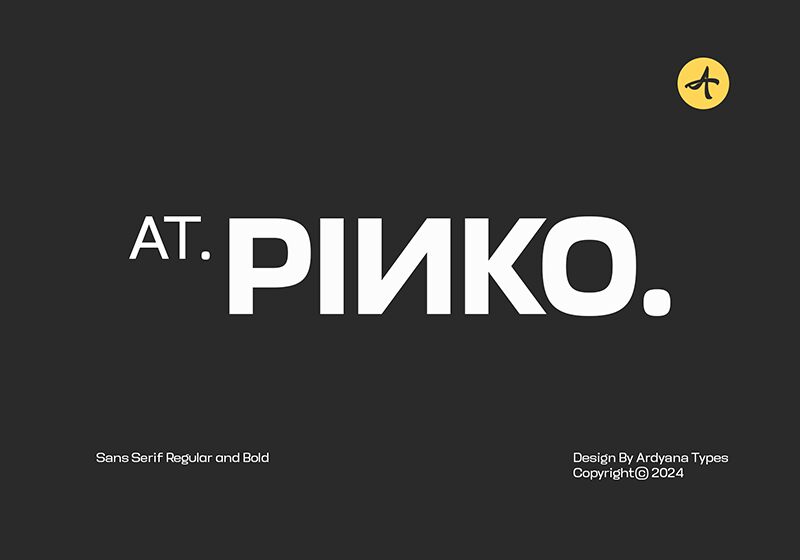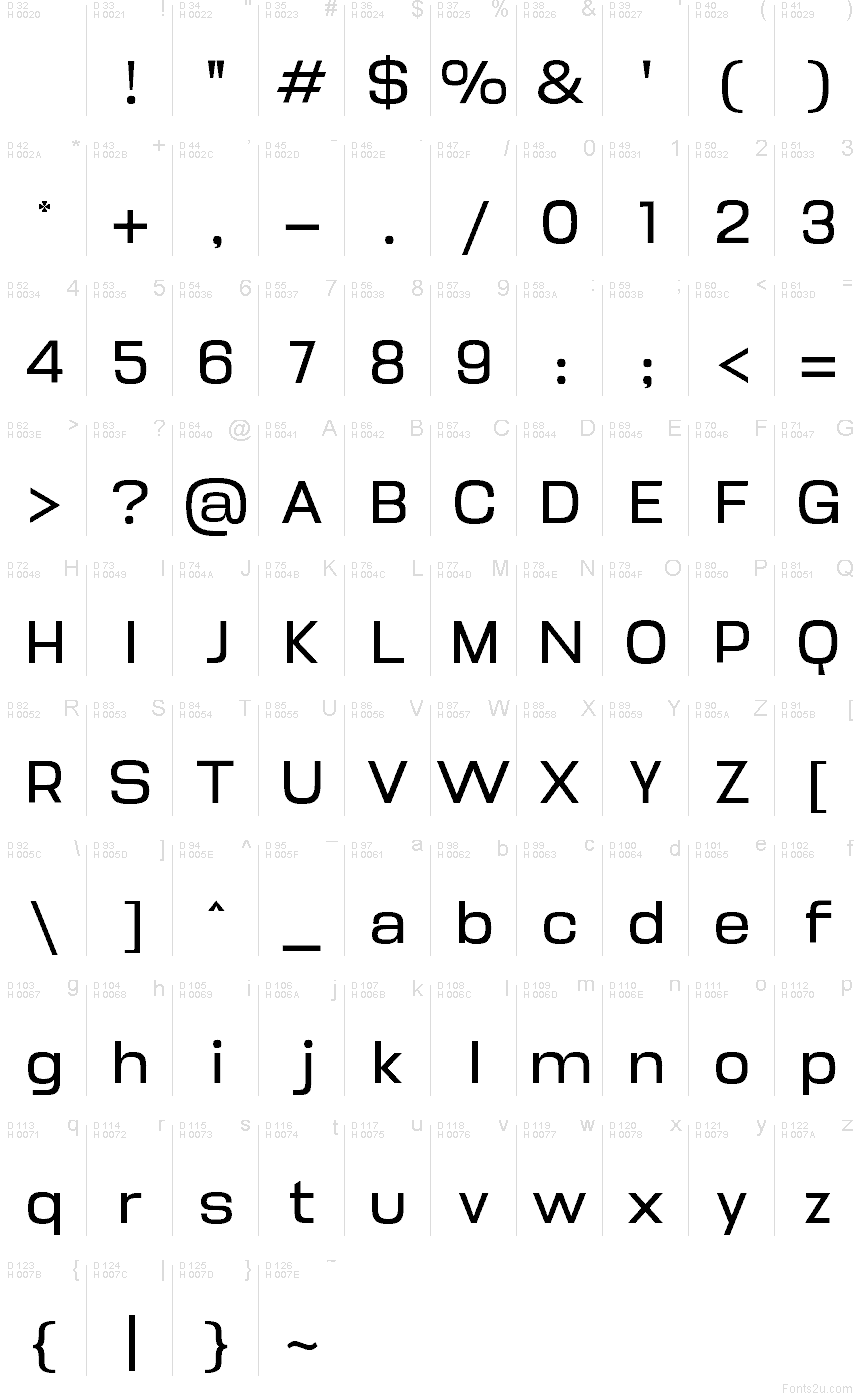
AT Pinko od Ardyanatypes je bezpatkové písmo zdarma s jednoduchou, geometrickou strukturou a hladkými, rovnoměrnými tahy. Písmena si udržují přímočarý rytmus s čistými rovnými liniemi, otevřenými křivkami a kompaktní tečkou, což rodině dodává úhledný, moderní tón.
AT Pinko je bezplatné písmo, které dobře funguje u log, brandingu, obalů, titulků na plakátech, krátkých popisků a redakčních prvků. Jeho prosté tvary bez ozdob udržují tyto výstupy přehledné a stabilní, zejména pokud layout vyžaduje bezpatkový font, který působí přímočaře, aniž by vypadal mechanicky.